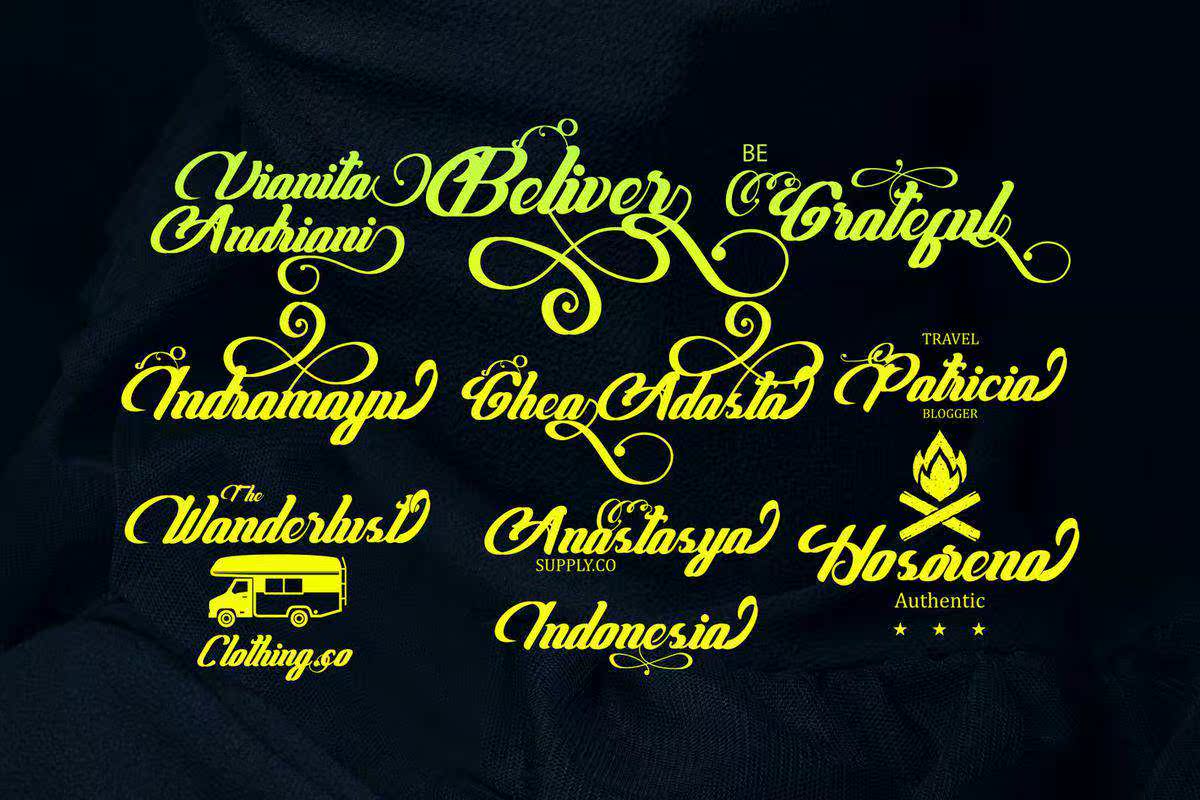
Gheaadastascript受Lifestyle和潮流排版的启发。我将其与我的手写字体风格相结合。让个性化触碰每一条曲线。我希望这能让你从工作中获得灵感。每一条Bouncy基线都能完美地完成对MarkerFont的赞美,以及对Bonusswash的赞美。理想的日志、手写引号、产品包装、标题、海报、商品、,社交媒体和问候卡。Gheaadastascript受Lifestyle和潮流排版设计的启发。我将其与我的手写字体风格相结合。让个性化触摸每一条曲线。我希望这能让你从工作中获得灵感。每一个Bouncy基线都有完美的装饰性标记字体,以及超硬和超硬的字体。理想的徽标、手写引号、产品包装、标题、,海报、商品、社交媒体和问候卡。